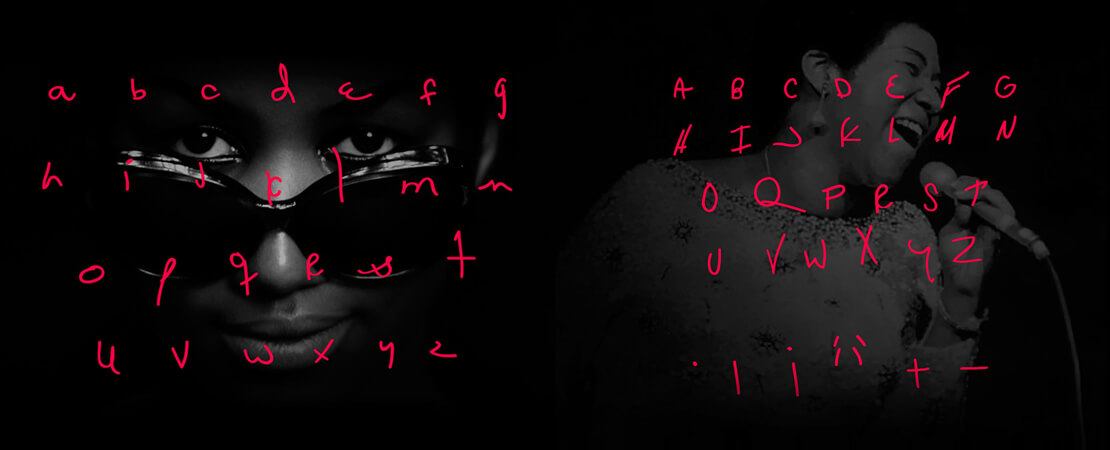
Aretha Franklin Tribute Free Font
Als Tribut an Aretha Franklin hat Nico Rubio einen Font entwickelt. Er basiert auf den handgeschriebenen Songtexten der Sängerin und kann kostenlos heruntergeladen werden.
Aretha Franklin Font Buchstaben vom Aretha Franklin Tribute Font
Aretha Franklin Tribute Free Font